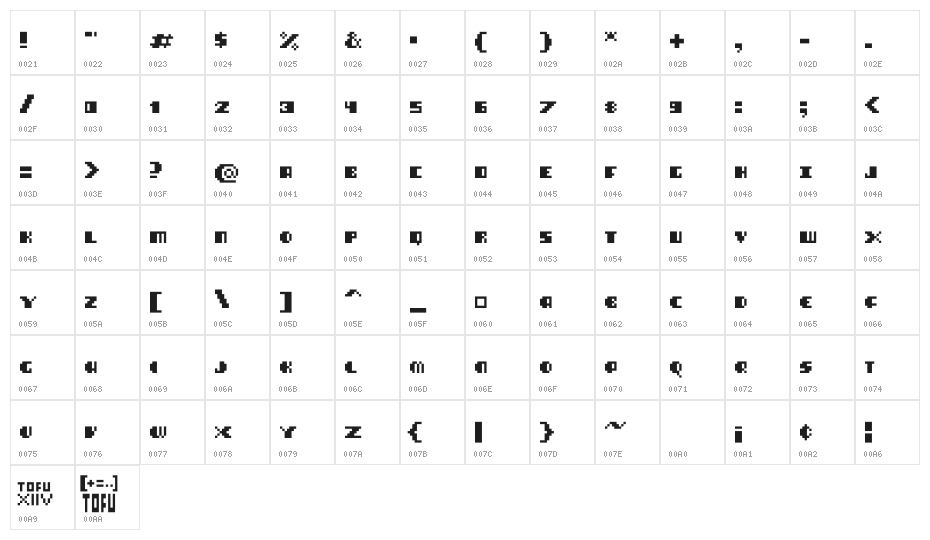
Blimpixels Font
| Caso d'uso | Headlines, Logos, Digital Art |
| Progetti proposti | Ideal for retro-themed designs, video game graphics, digital art projects, and any creative work seeking a nostalgic, digital aesthetic. |